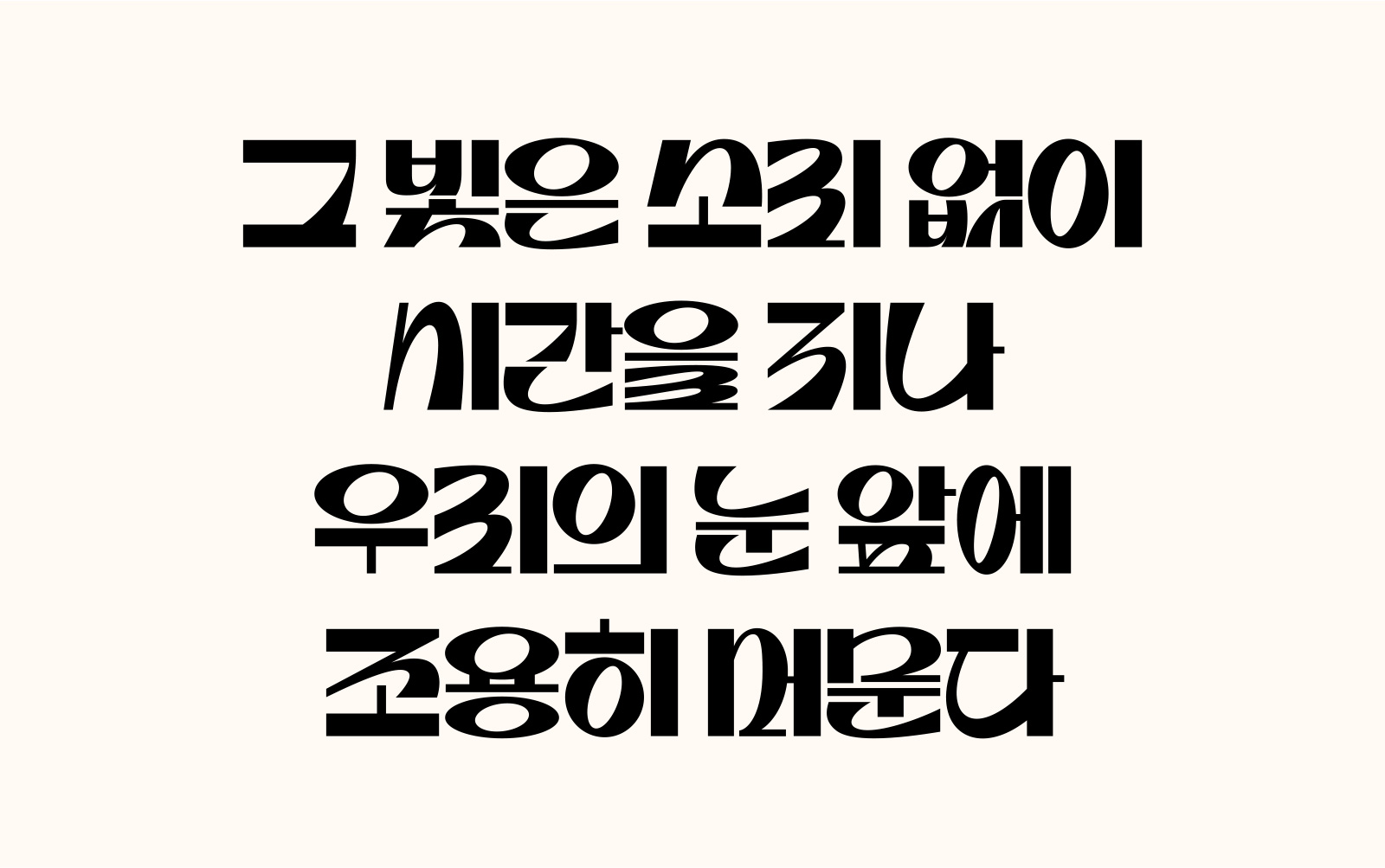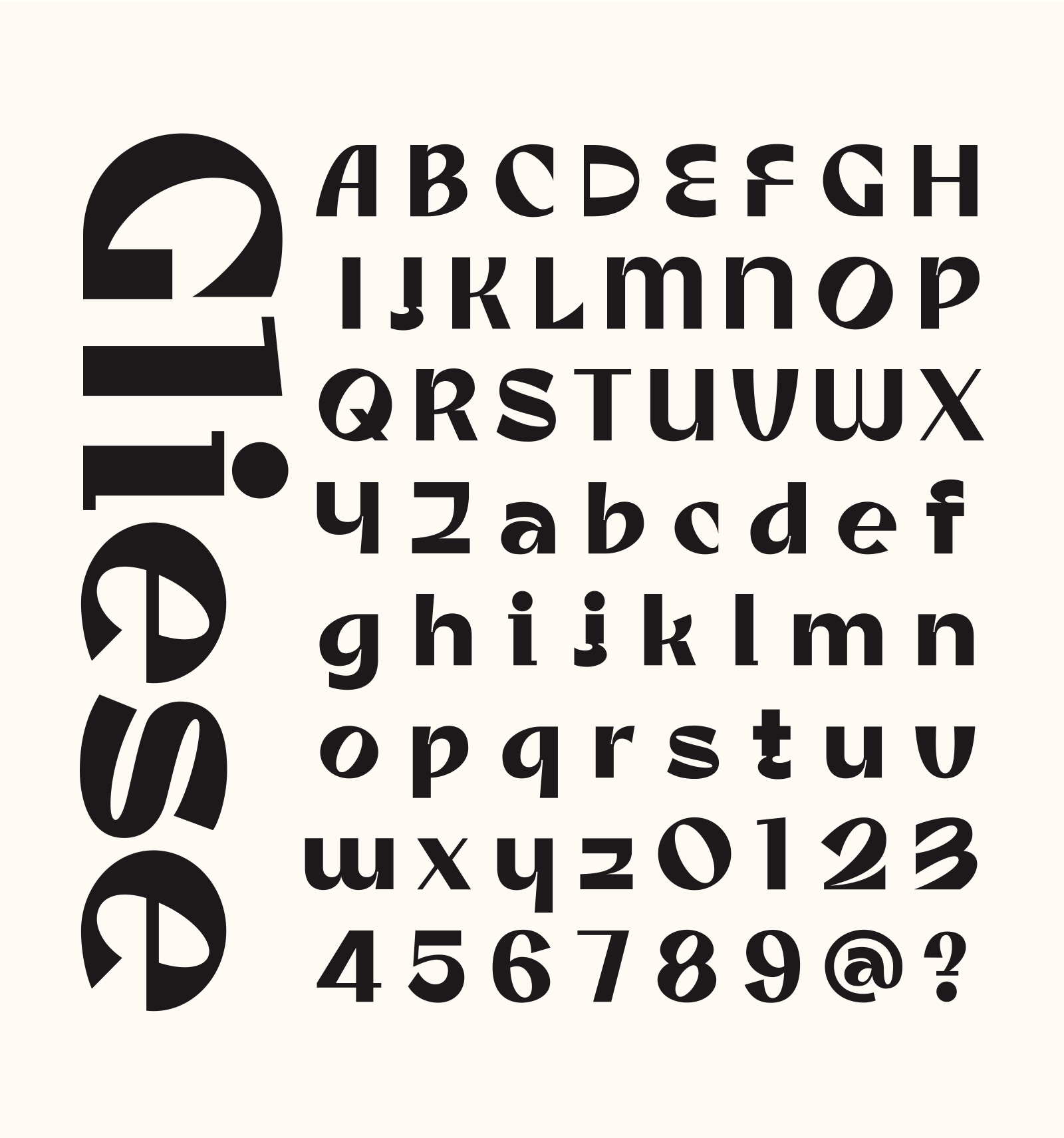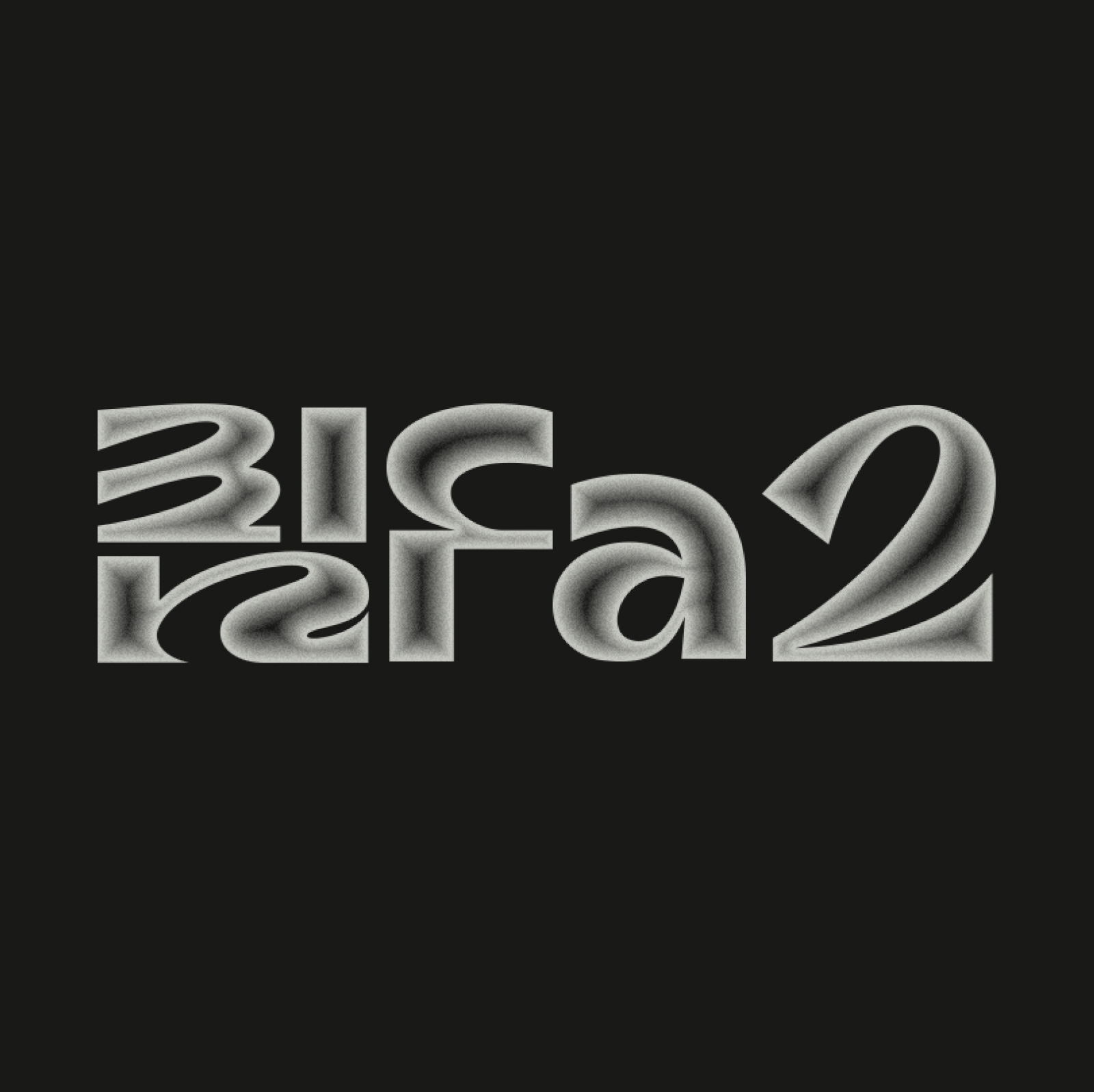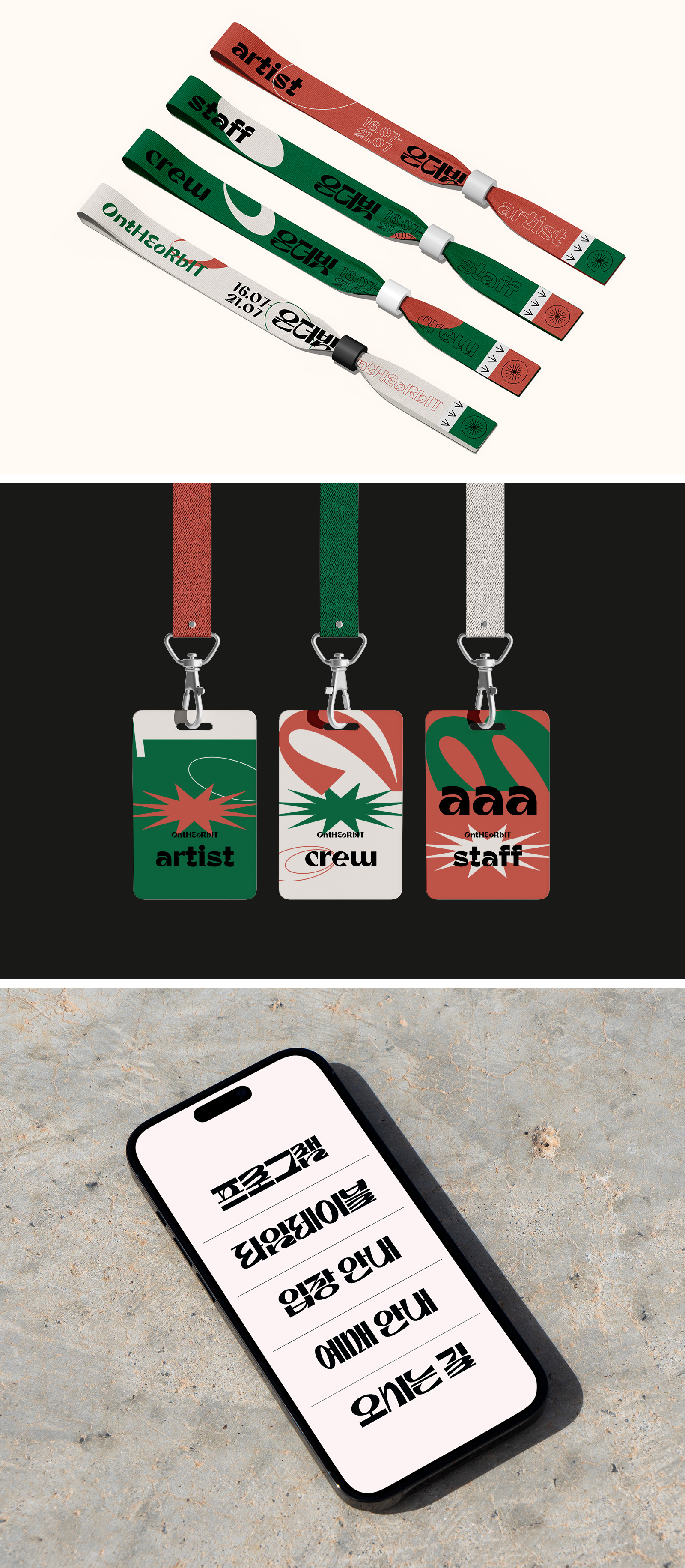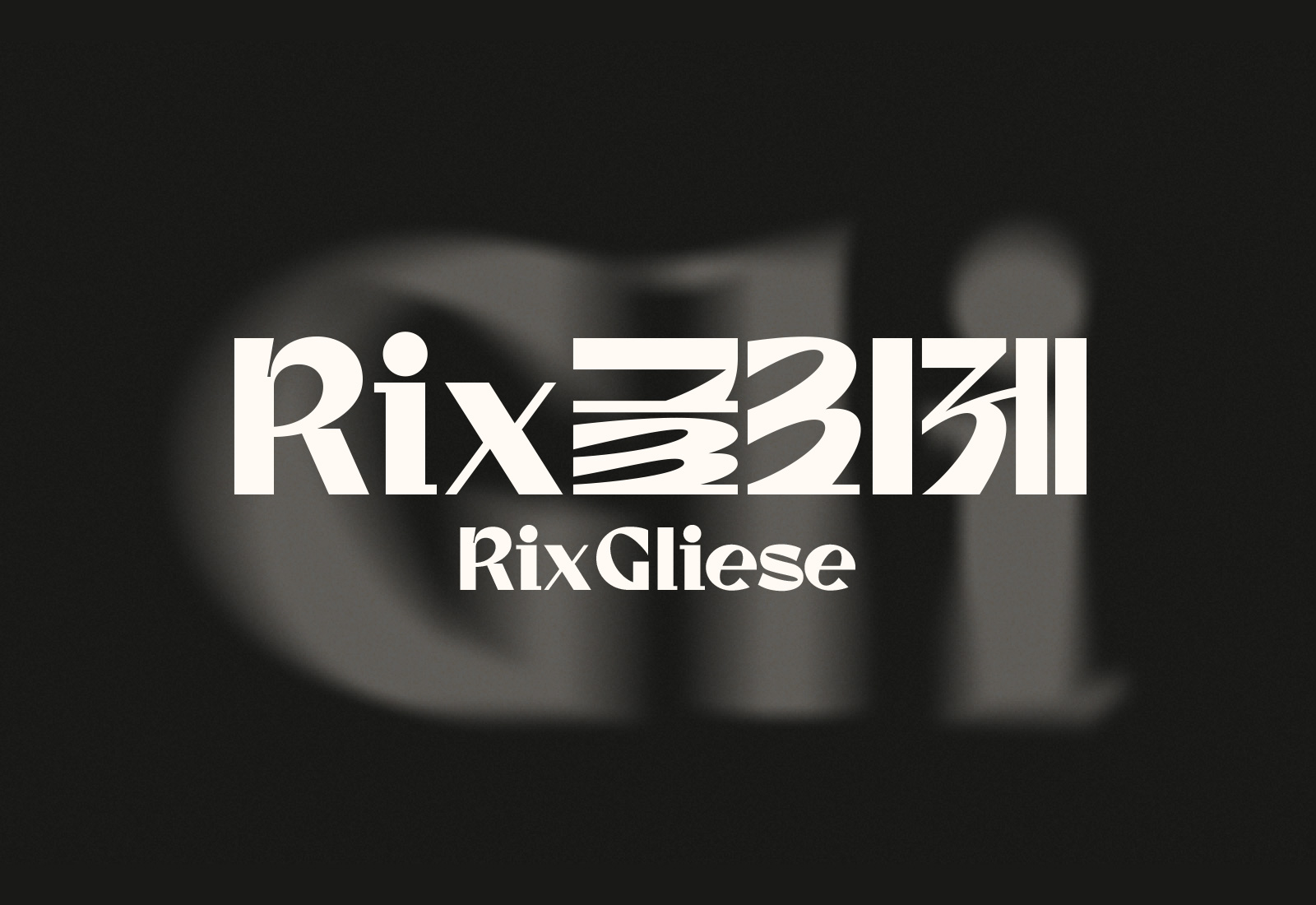
RixGliese
1 Style - RegularRix글리제는 글자 폭이 넓고 꾸밈요소가 많은 스타일의 제목용 서체입니다.
개성있는 자소 형태와 강한 대비로 시선을 끄는 것이 특징입니다.
| FontFamily | Rix글리제 / RixGliese |
|---|---|
| Design | Yu Hyun-Ju |
| Direction | Park Yong-rak |